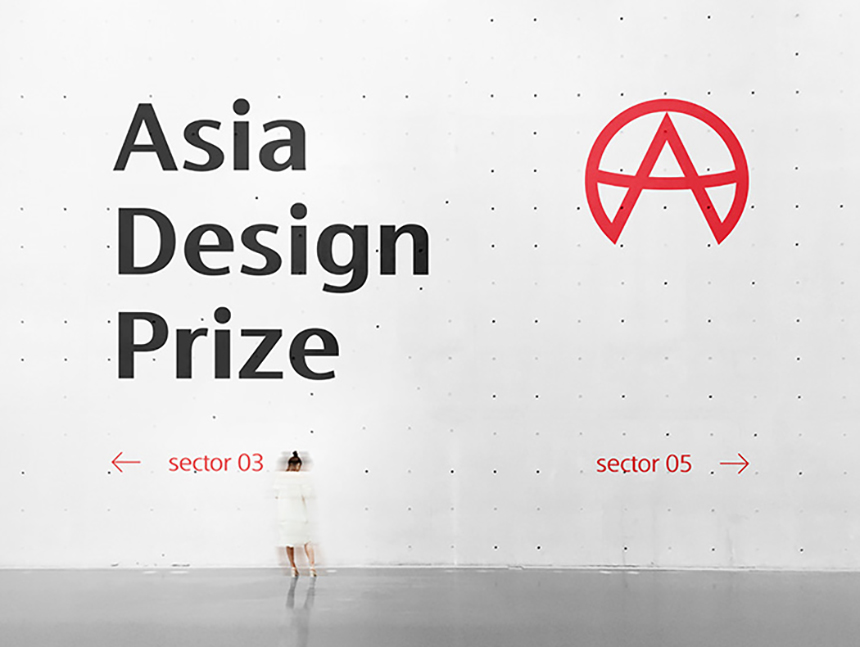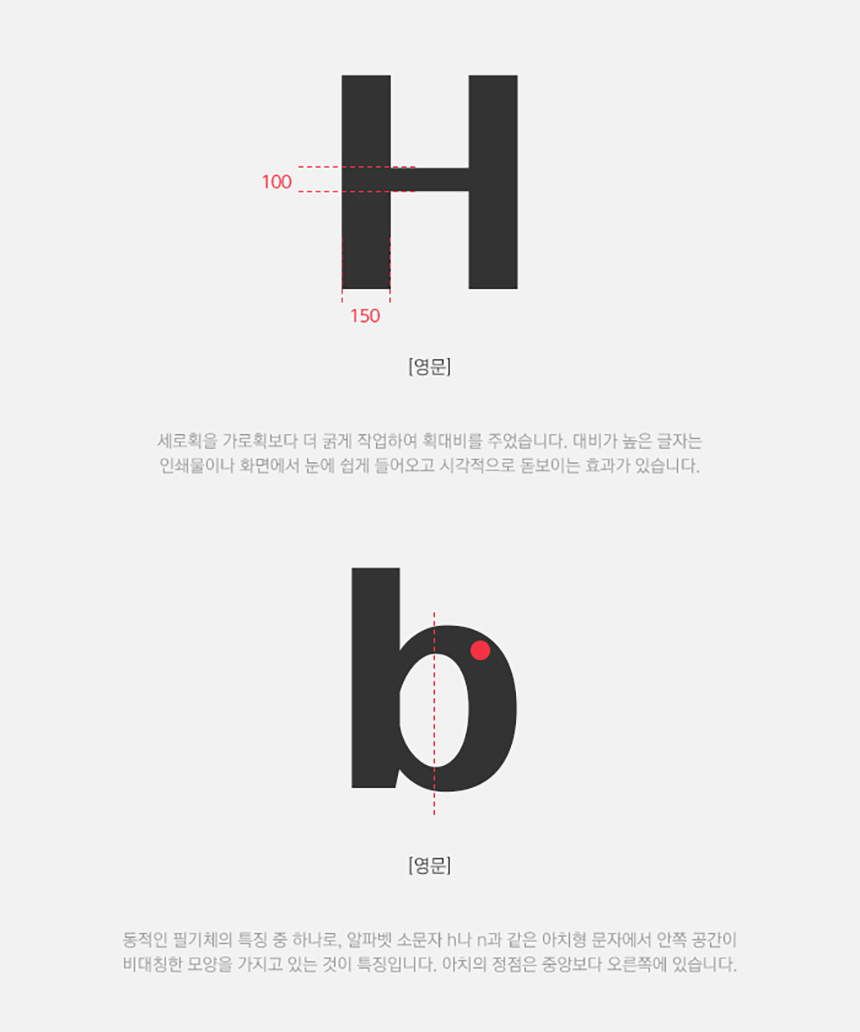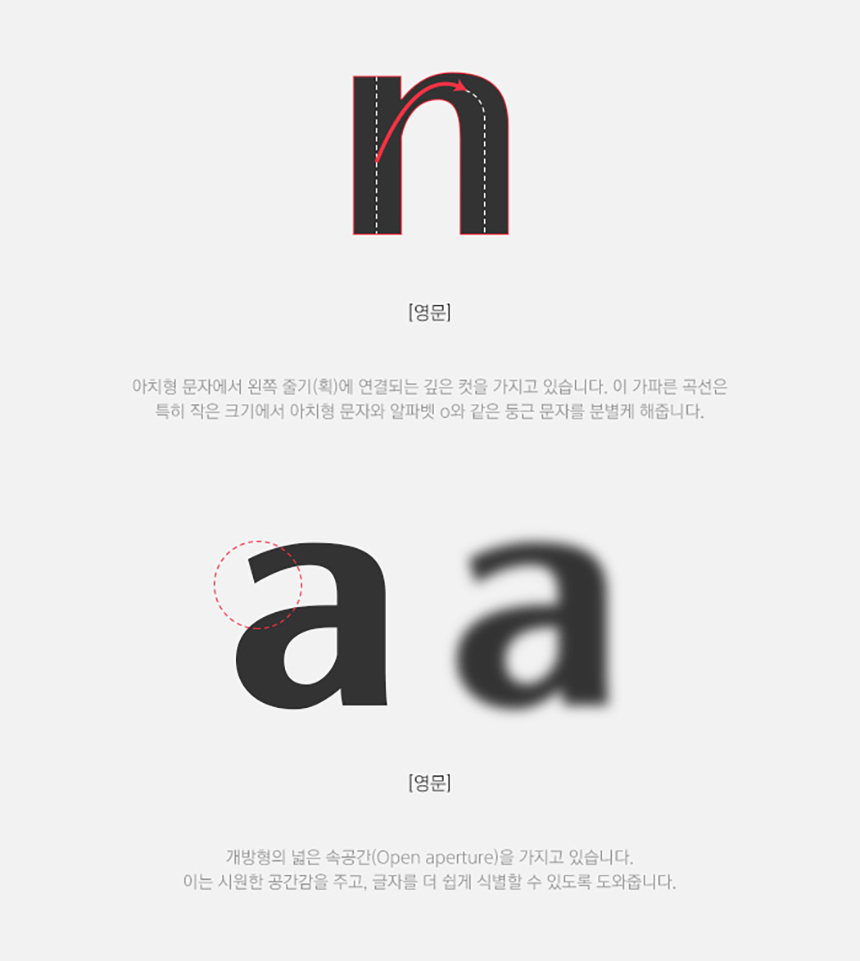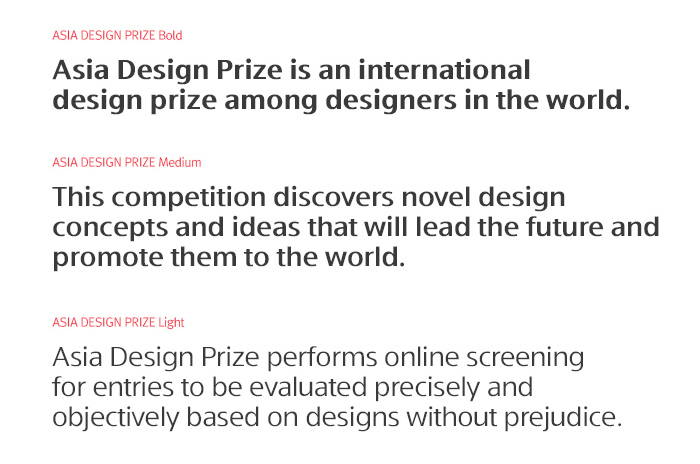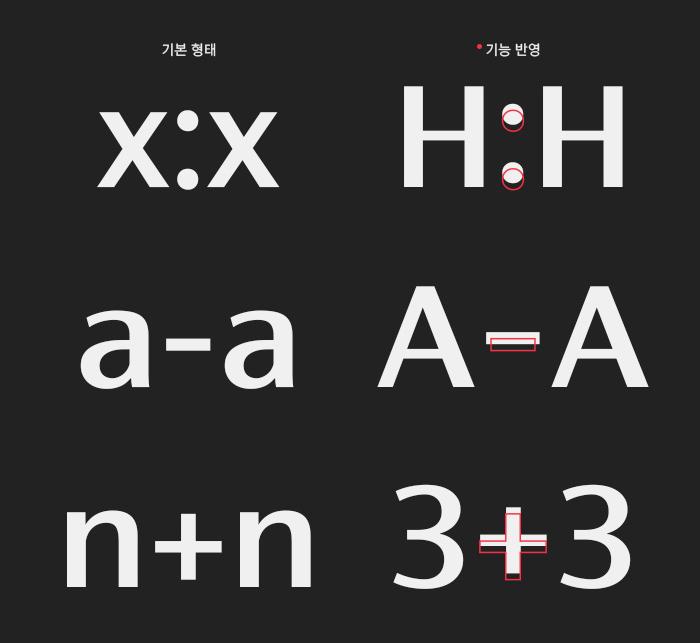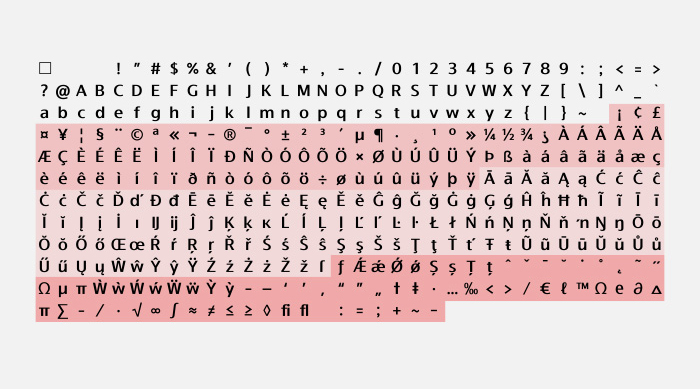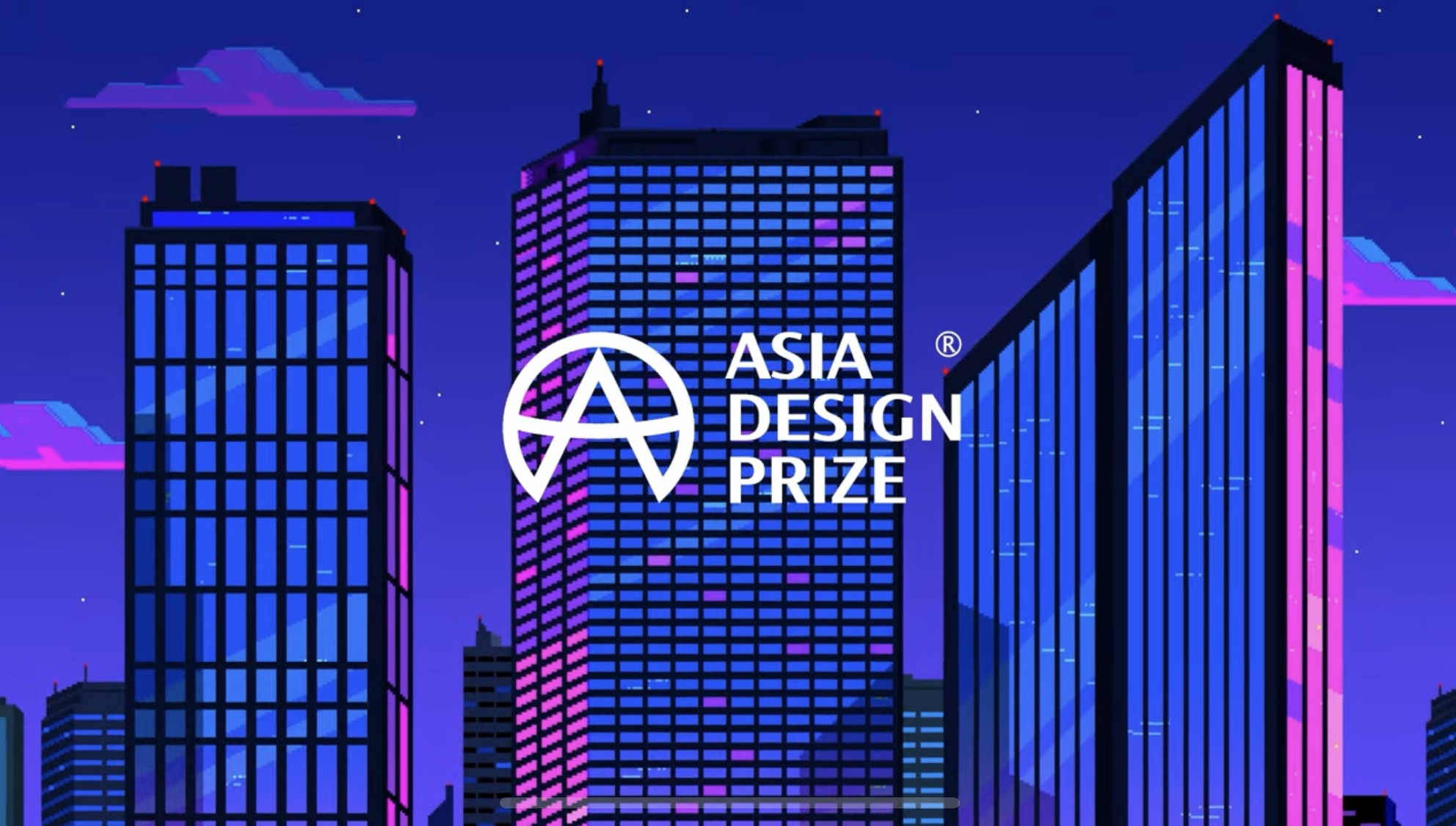
오늘 알아볼 전용서체는 국제적으로 이름을 알리고 있는 아시아 최대 규모 디자인 공모전 아시아 디자인 프라이즈의 전용서체로 제작된 「Asia Design Prize」영문 서체입니다. 아시아 디자인 프라이즈의 제안으로 폰트릭스에서 전용서체 기획부터 제작까지 함께 진행했던 사례로, 올해 10월 출시되어 무료로 배포된 따끈따끈한 신규 폰트인데요. 어떻게 제작되었는지, 또 어떤 특징이 있는 서체인지 소개해 드리려고 합니다.
디자이너가 인정한 영문 서체
폰트릭스는 주로 국내 기업의 한글 전용서체를 제작해왔기 때문에 이번 서체 제작에 있어서 외국인의 시각으로 봐도 완성도 있고 퀄리티 있는 영문 서체를 만드는 것을 목표로 했습니다. 디자이너가 보아도 멋진 서체, 디자인 감성이 녹아든 서체를 제작하기 위해 고민하여 고딕에 획의 대비와 손맛을 가미한 서체를 만드는 데 무게를 두고 제작했습니다.
휴머니스트 산스 서체의 하나로서 이 폰트는, 특징성을 가지는 동시에 다양한 상황에 적용될 수 있도록 하겠다는 목적을 충실히 만족시킨다. 또한 두께와 곡선이 유려하고 시상식에 잘 어울린다. 다른 폰트 영상들과 달리 보는 이들이 이해하기 쉽도록 서체의 생기와 특징을 잘 보여 준 소개 영상도 눈에 띈다. 마치 긍정적이고 진보적인 아시아 디자인 프라이즈의 미래를 보여 주는 듯하다.
Karim Rashid 카림 라시드 서체평
세계적인 디자이너이자 아시아 디자인 프라이즈(이하 ADP)의 심사위원장인 카림 라시드는 서체에 대해 이렇게 평을 남겨주었습니다. 그의 말에서도 알 수 있듯 휴머니스트 산스로서의 디자인적인 부분뿐 아니라 다양한 환경에서의 최적화가 동시에 가능하도록 개발된 서체입니다.
휴머니스트 산스, 디자인 그 너머
서체 제작의 가장 기본이 되는 포지셔닝 단계에서 *휴머니스트 산스 계열로 기획을 하게 되었습니다. 사람의 손맛이나 감성이 살아있는 서체 스타일로 제작함으로써 아이덴티티가 느껴지면서도 기하학적인 고딕의 형태와 굵기 대비, 손글씨의 맛을 살리는 접점을 찾고자 노력했습니다.
*휴머니스트 산스(Humanist Sans)
르네상스 시대 필기체의 특징이 남아있는 고딕체로 가로, 세로의 두께 대비가 조금 더 있는 산스 계열 서체.
최적의 굵기 대비와 손맛을 구현하는 데 많은 시간을 투자했으며, ADP만의 특징이 드러나도록 자소에 대한 연구와 함께 완성도를 최대로 끌어올리는 작업을 했습니다. 알파벳마다 글자를 잘 식별할 수 있도록 적절한 획대비 및 공간감을 주는 것도 고려한 부분입니다.
활용도를 고려한 친절한 서체
ADP 전용서체는 총 3가지 두께로 파생하여 용도에 따라 활용하기에 좋습니다. 제목용으로 적합한 굵은 두께의 Bold, 중 제목용이나 자막에도 활용하기 좋은 Medium, 모바일이나 PC 화면용 본문 텍스트에 최적으로 설정한 Light로 구성하여 각 굵기마다 가독성을 놓치지 않으면서 디자인적인 특징이 드러나도록 제작했습니다.
또한 자연스러운 글줄의 흐름을 위해 리가처 기능(Ligature: 조건에 따라 글자의 형태를 변환할 수 있는 기능)을 일부 기호에 추가하여, 소문자/대문자, 숫자 및 글자가 함께 쓰였을 때 중심 높이를 맞출 수 있도록 했습니다.
Latin 문자 영역 확장으로 유럽 언어권 대부분에서 사용이 가능하도록 개발했습니다. 여러 활용도를 고려하여 많은 분들이 조금 더 쉽고 다양하게 서체를 사용할 수 있도록 완성도를 높였습니다.
Asia Design Prize 영문 서체의 활용
아시아 디자인 프라이즈 CI로도 사용된 Bold체는 제목용으로 주로 활용되고 있습니다. 타이틀에 적합하도록 자간이 다소 좁게 설정되어 있으니 콘텐츠에 따라 자간을 적절히 조절하여 사용하는 것이 좋습니다.
써볼수록 높은 완성도와 매력을 느낄 수 있는 ADP 전용서체. 디지털, 인쇄물 등 다양한 환경에서 잘 읽히고 고급스럽게 표현됩니다. 현재 RixFont 클라우드에서 무료로 사용해 볼 수 있으니 직접 써보시는 것을 추천드립니다⌨